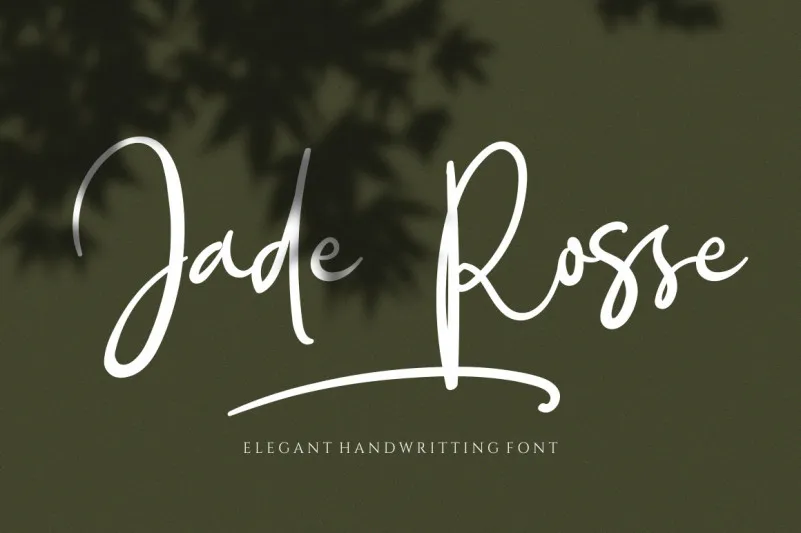
Jade Rosse Font – Fonte Grátis
Jade Rosse Font
Esta é uma fonte script elegante e delicada, perfeita para quem valoriza sofisticação e refinamento em seus projetos digitais. Esta fonte tem PUA (Unicode Plane Extensions) encoded, isso significa que você pode acessar facilmente todos os gílios e swashes sem dificuldades. Adoraremos a sua versatilidade e estaremos ansiosos para vê-la transformando seus designs em obras de arte impressionantes! A fonte ‘Jade Rosse’ é criada pelo designer ReyreyBlue, que oferece uma variedade incrível de opções de layout que podem ser usadas de diversas maneiras. Seja você um profissional de design ou simplesmente alguém apreciando uma nova ferramenta para expressar seu trabalho de design, essa fonte pode revolucionar a forma como você cria e compartilha suas ideias.